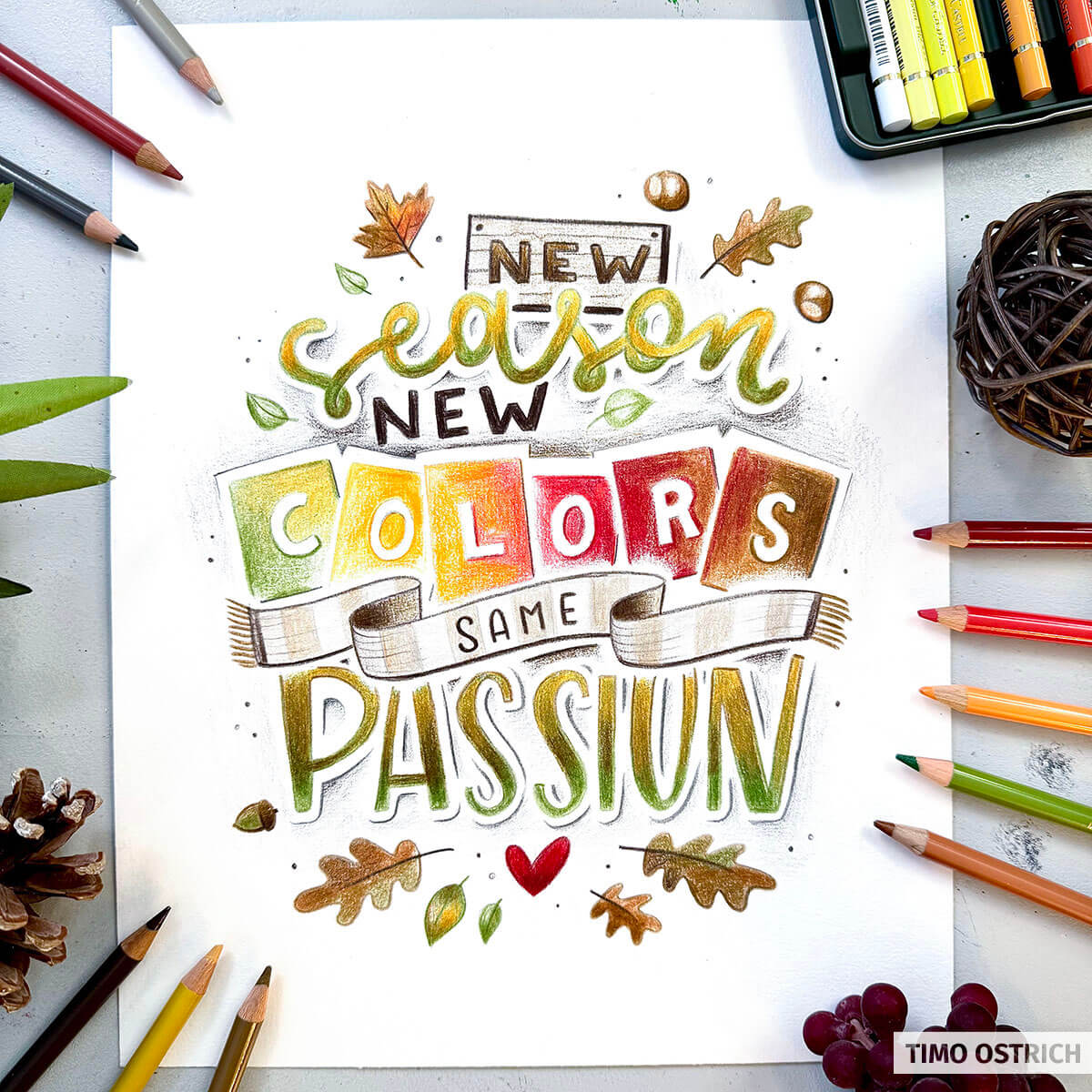
New Season New Colors Same Passion
Eine bunte Handlettering-Komposition mit herbstlichen Farben und vielen Farbverläufen. In diesem Fall wurden ausschließlich Buntstifte genutzt, sodass der unvergleichliche Look eines Pencil-Letterings entsteht.